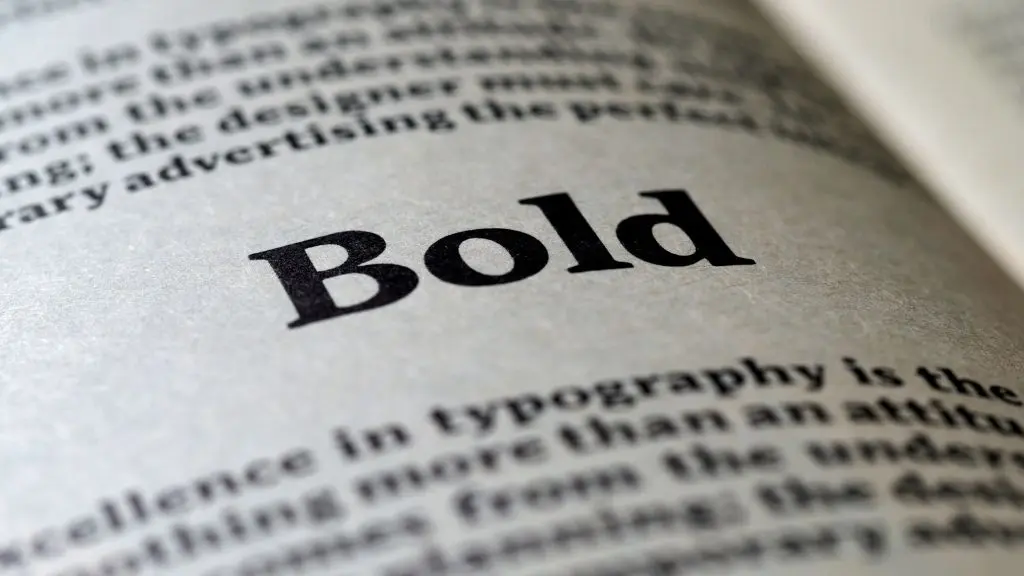
En el entorno del diseño, la elección de la tipografía adecuada para un anuncio es fundamental para transmitir el mensaje deseado y crear la identidad visual correcta. Una tipografía bien seleccionada puede marcar la diferencia entre un anuncio memorable y uno que pasa desapercibido. Este artículo te guiará a través de los métodos para identificar la tipografía de cualquier anuncio, incluyendo herramientas online y consejos para obtener resultados precisos.
Elementos clave para identificar una tipografía
Antes de recurrir a las herramientas digitales, es importante observar detenidamente los caracteres de la tipografía. Presta atención a los siguientes detalles:
- Forma y estilo general: Observa la altura de las letras, la inclinación (cursiva o romana) y la presencia o ausencia de serifas (pequeños remates en los extremos de las letras).
- Estructura y consistencia: Analiza la estructura general de los caracteres y la uniformidad en su diseño. ¿Son las letras proporcionales entre sí? ¿Mantiene un estilo consistente a lo largo del texto?
- Proporciones: Examina las proporciones de las letras, la relación entre sus partes más anchas y estrechas. Esto te ayudará a distinguir entre diferentes familias tipográficas.
- Espaciado: Observa el espaciado entre letras (kerning) y palabras (tracking). Un espaciado inadecuado puede afectar la legibilidad y la estética general.
- Características especiales: Fíjate en la presencia de ligaduras (uniones de dos o más letras) o en letras con remates o detalles especiales. Estos elementos pueden ser claves para identificar la tipografía .
Herramientas online para identificar tipografías
Existen varias herramientas online que te ayudarán a identificar la tipografía de un anuncio. Algunas de las más populares son:
WhatTheFont
WhatTheFont es una herramienta popular que te permite subir una imagen con el texto cuya tipografía deseas identificar. El sistema analizará la imagen y te proporcionará una lista de posibles coincidencias. Recuerda que la precisión de los resultados depende de la calidad de la imagen y de la claridad del texto.
What Font is
Similar a WhatTheFont, What Font is permite subir una imagen o una URL y señalar el texto a analizar. Una ventaja de esta herramienta es la posibilidad de filtrar las fuentes gratuitas, facilitando la búsqueda si necesitas una opción sin costo.
WhatFont (Extensión de Chrome)
Si utilizas Chrome, la extensión WhatFont te permite identificar la tipografía de cualquier texto en una página web simplemente pasando el ratón sobre él. Esta opción es muy práctica para identificar fuentes en sitios web.
Google Font Previewer for Chrome (Extensión de Chrome)
Esta extensión de Chrome te permite previsualizar diferentes fuentes en una página web, lo que te facilita comparar diferentes opciones y elegir la que mejor se adapta a tus necesidades. No identifica directamente la tipografía, pero facilita la búsqueda de alternativas.
Find my Font (App Móvil)
Disponible para Android e iOS, Find my Font funciona de forma similar a las herramientas web: subes una imagen y la app te proporciona una lista de posibles coincidencias.
FontSquirrel Matcherator
FontSquirrel, además de ofrecer una gran biblioteca de fuentes gratuitas, cuenta con Matcherator, una herramienta que identifica fuentes a partir de imágenes. Su funcionamiento es parecido a WhatTheFont.
Identifont
Identifont es diferente a las otras herramientas, ya que no utiliza imágenes. Te realiza una serie de preguntas sobre las características de la tipografía, guiándote a través de un proceso de eliminación para identificar la fuente.
Aplicaciones móviles para identificar tipografías
Para usuarios de dispositivos móviles, existen aplicaciones que facilitan la identificación de tipografías directamente desde el teléfono o la tablet:
- WhatTheFont (App móvil): Versión móvil de la popular herramienta web.
- FontSnap: Otra aplicación con un funcionamiento similar a WhatTheFont.
Consejos para mejorar la precisión
Para obtener resultados más precisos al identificar tipografías, considera los siguientes consejos:
- Imágenes de alta calidad: Utiliza imágenes con buena resolución y un texto claro y legible.
- Texto claro y legible: Evita imágenes borrosas o distorsionadas.
- Fuentes simples: Las herramientas funcionan mejor con fuentes simples y claras, evitando estilos decorativos o cursivos complejos.
- Recortar la imagen: Recorta la imagen para que solo contenga el texto que deseas identificar, eliminando elementos de fondo que puedan interferir.
Consultas habituales
¿Es posible identificar cualquier tipo de letra con estas herramientas?
No siempre. Las herramientas son muy precisas, pero puede que no logren identificar fuentes exclusivas o muy personalizadas. Sin embargo, ofrecen alternativas muy similares.
¿Qué hago si no puedo identificar la fuente exacta?
Si ninguna herramienta te da un resultado exacto, prueba con las sugerencias más cercanas o busca fuentes similares en bibliotecas como Google Fonts o Adobe Fonts.
| Identifont | Web | Web | Basada en preguntas, útil si se recuerdan características | No utiliza imágenes |
Con esta información y las herramientas descritas, podrás identificar con mayor facilidad la tipografía de cualquier anuncio y utilizarla en tus propios diseños. Recuerda que la práctica y la observación detallada son claves para mejorar tus habilidades en la identificación tipográfica.